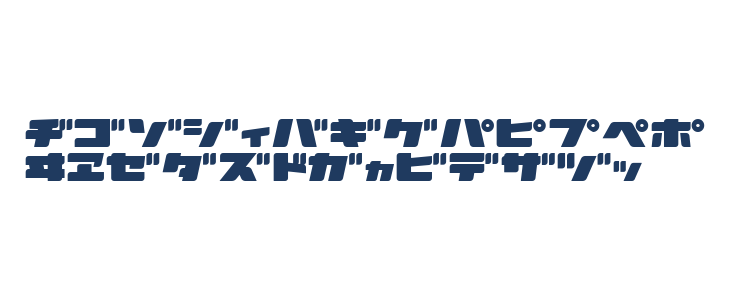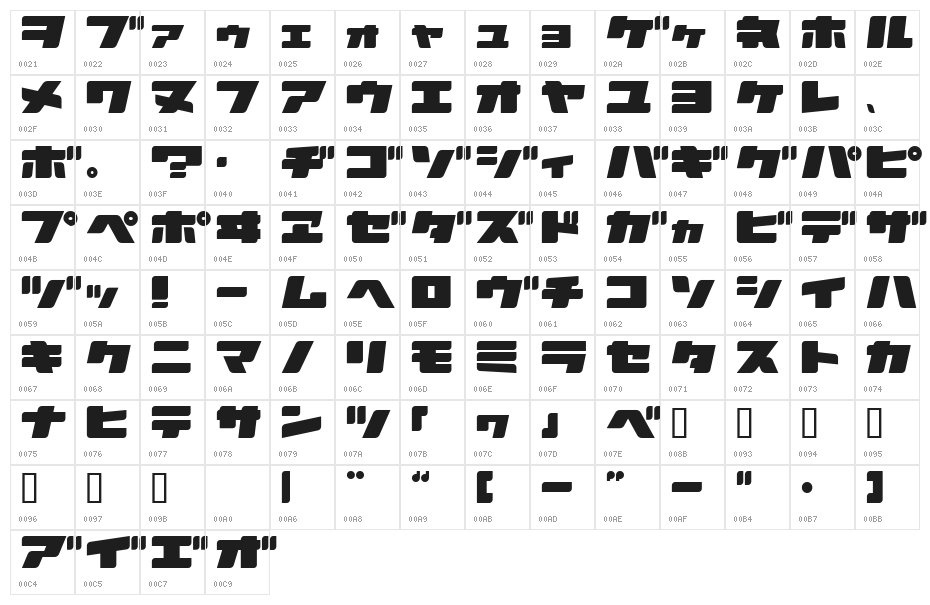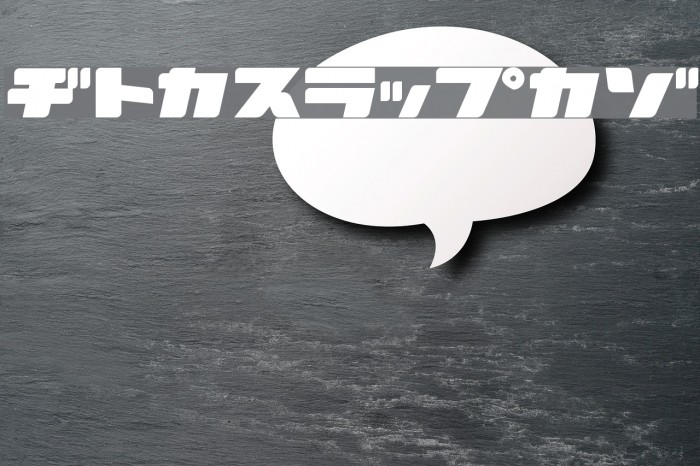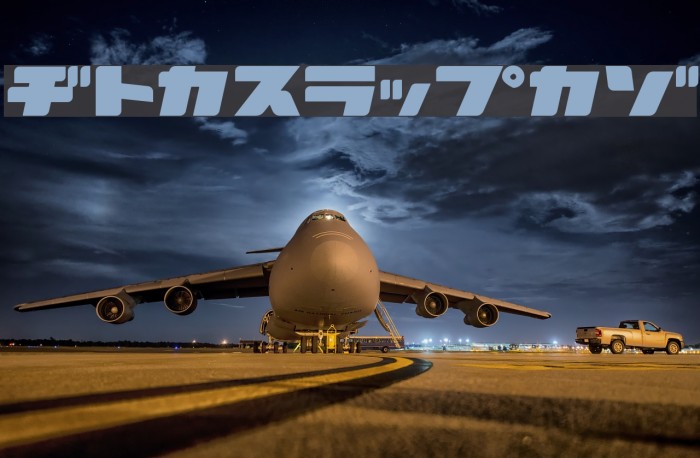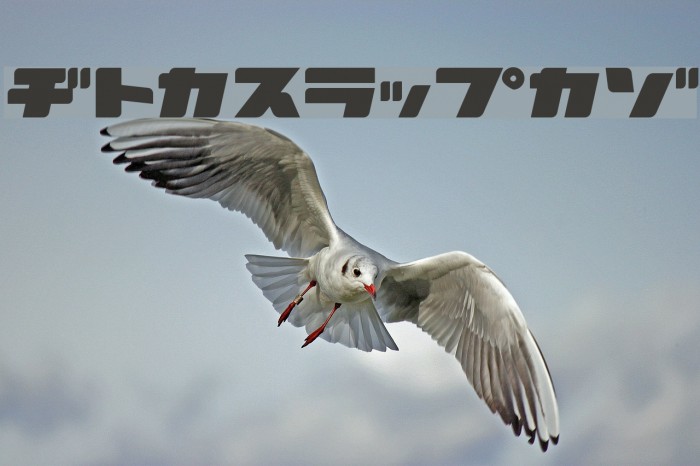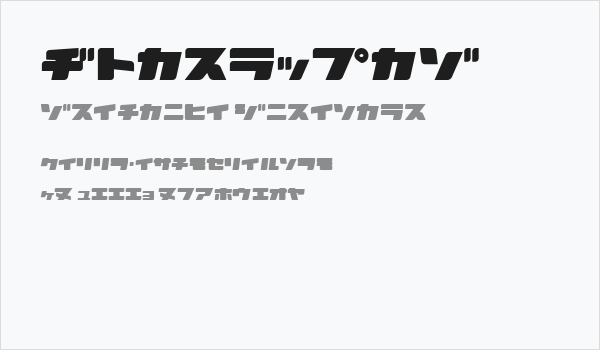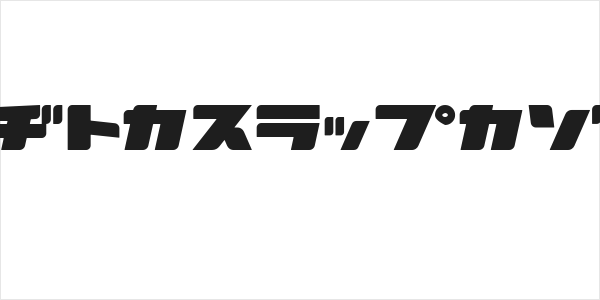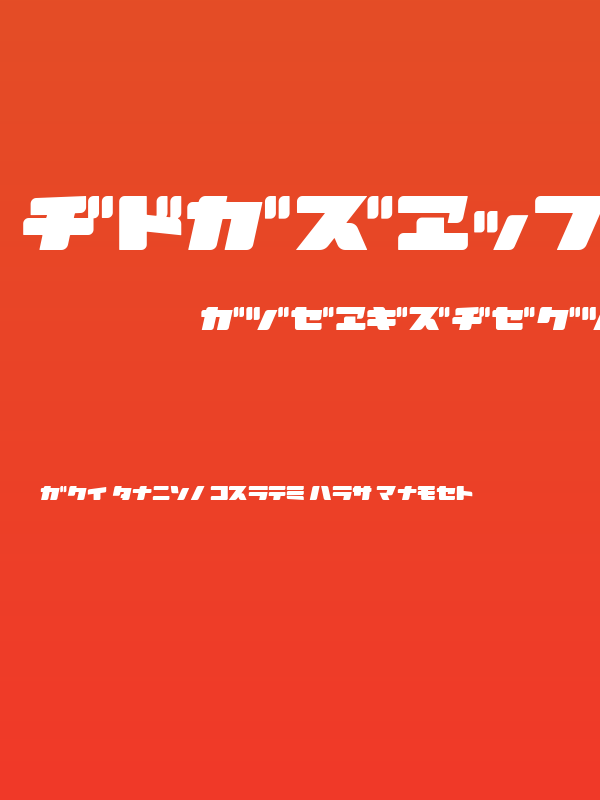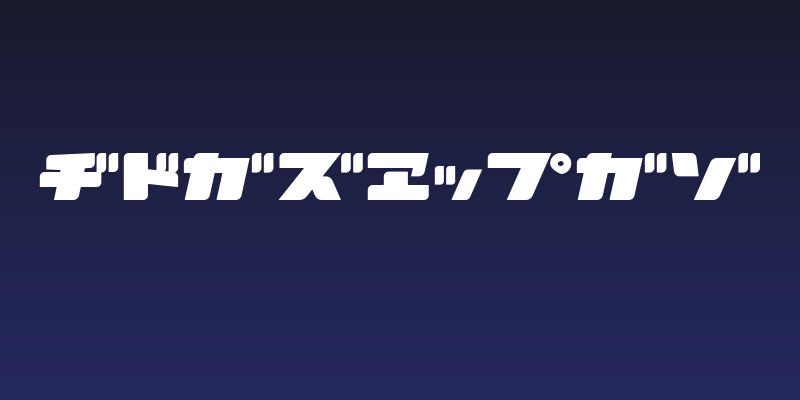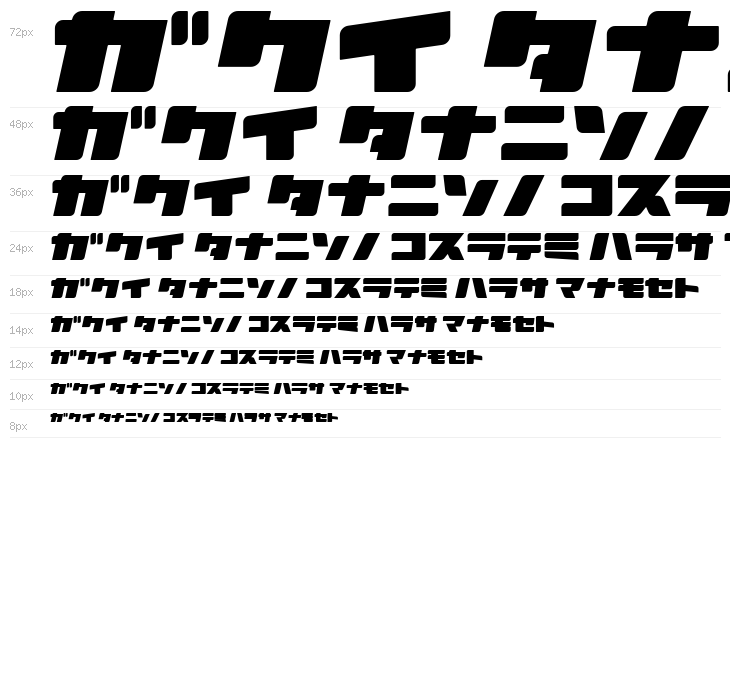
AstroZKtC Font
| Stile generale | Retro, Modern |
| Progetti proposti | This font is perfect for projects that require a strong visual impact, such as posters, logos, branding materials, and advertising campaigns. Its boldness and clarity make it suitable for both digital and print media. |